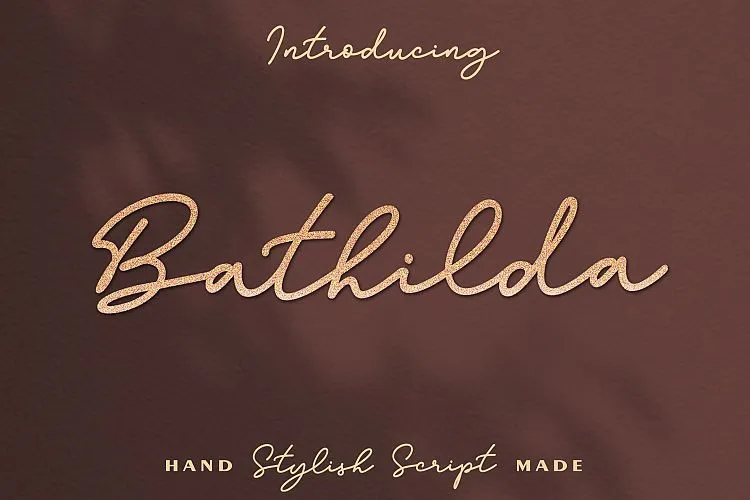
A Bathilda Font é uma delicada tipografia escrita a mão, criada pelo designer Hamilton para blogueiros, crafters e designers. Esta fonte mono linha tem um estilo elegante e letra cuidadosamente escrita. Ela é perfeita tanto para logotipos quanto para convites de casamento, assinaturas e muito mais. Com uma leitura agradável e sem erros, Bathilda é um recurso valioso para quem busca uma fonte escrita a mão em seu projeto gráfico. Ideal para aqueles que valorizam o estilo natural da escrita humana em seus designs.